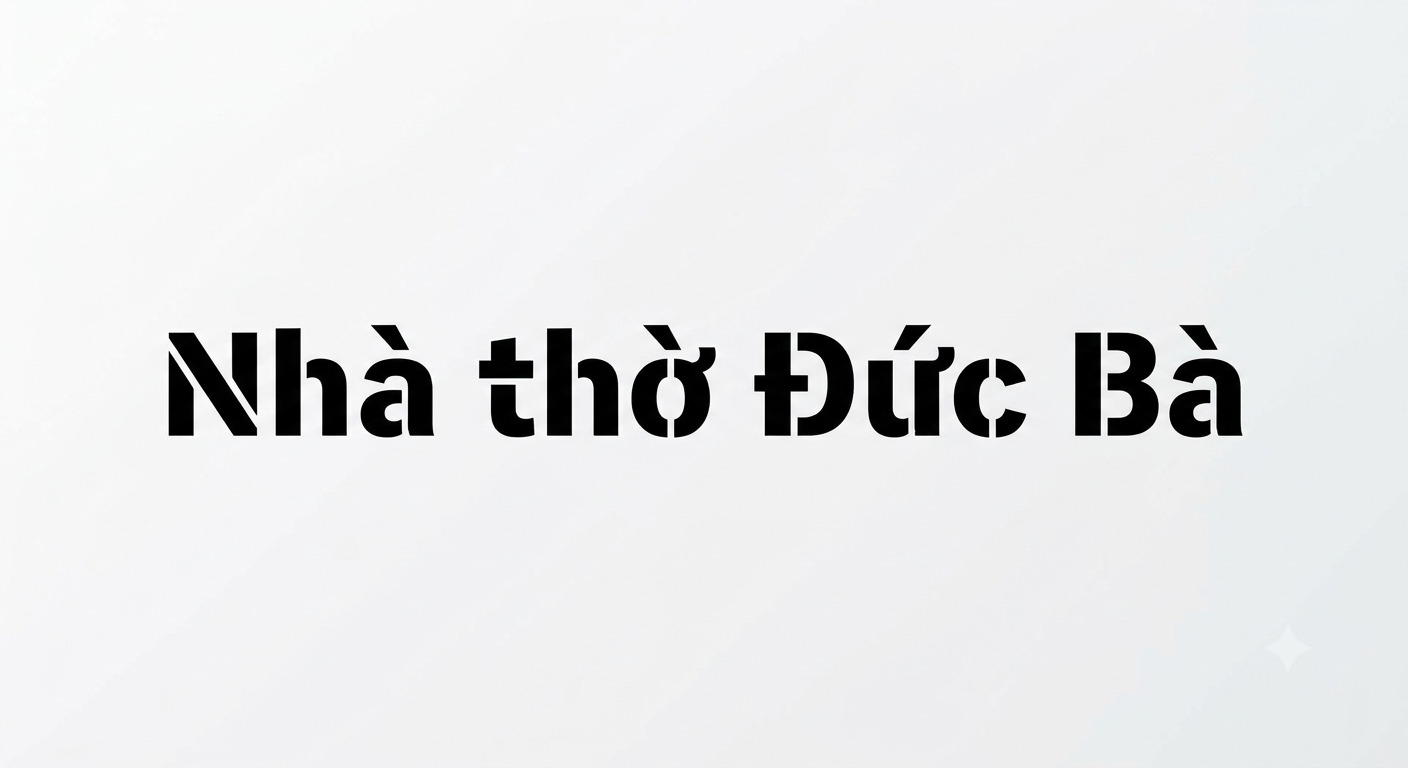
Font Stencil Việt hóa (hay còn gọi là phông chữ khuôn mẫu, nét đứt đoạn) là nhóm các phông chữ mô phỏng lại các ký tự được sơn xịt qua tấm khuôn (shablon) trên các thùng hàng vận chuyển quân sự và công nghiệp. Với đặc trưng là các đường nét bị cắt đứt quãng có chủ đích, phông chữ Stencil mang lại diện mạo thô mộc, mạnh mẽ, cá tính và đậm chất thực dụng. Doozypack.vn cung cấp link Tải Font Stencil trọn bộ chuẩn kỹ thuật, giúp bạn sở hữu phông chữ độc đáo này, hỗ trợ đầy đủ tiếng Việt để tự tin thiết kế bao bì, nhãn mác và bộ nhận diện thương hiệu.
Đặc điểm thẩm mỹ độc đáo của bộ font Stencil
Font Stencil không đi theo sự liền mạch của các phông chữ thông thường; nó tạo ra một ngôn ngữ thị giác đầy tính công nghiệp, gợi nhắc đến thế giới của logistics, quân đội và các xưởng cơ khí.
Phong cách cắt đứt (Stenciled) mang đậm dấu ấn quân sự và vận tải
Đặc trưng lớn nhất của Font chữ Stencil là các nét ngang và dọc bị ngắt quãng tại những điểm giao nhau. Kỹ thuật này vốn sinh ra để tấm khuôn kim loại không bị rơi rớt phần lõi khi khắc chữ lên thùng hàng. Trong thiết kế đồ họa, khoảng trống (gaps) này trở thành một điểm nhấn thẩm mỹ vô cùng đắt giá, giúp tiêu đề bản thiết kế toát lên vẻ gai góc, thực dụng và mang hơi hướng đường phố (Military & Streetwear).
Cấu trúc chữ vững chãi tối ưu cho các tiêu đề mạnh mẽ
Hầu hết các biến thể phổ biến như Font SVN Stencil đều sở hữu cấu trúc chữ in hoa (All-caps) với độ dày nét (weight) lớn. Trục chữ thẳng đứng vững chãi giúp các dòng tiêu đề giữ được độ dễ đọc tuyệt vời ngay cả khi được in trên các bề mặt thô ráp như thùng carton sóng hoặc túi giấy Kraft.
Ưu điểm nổi bật của bản SVN Stencil Việt hóa
Khi ứng dụng các phông chữ khuôn mẫu quốc tế vào thị trường trong nước, sự chỉn chu về dấu câu là yếu tố quyết định đến tính chuyên nghiệp của ấn phẩm:
- Khắc phục triệt để lỗi dấu tiếng Việt: Phiên bản SVN Stencil Việt hóa đã được đội ngũ thiết kế trau chuốt thủ công từng dấu câu. Các dấu sắc, huyền, hỏi, ngã, nặng được cắt đứt quãng đồng điệu cùng thân chữ gốc, không gây cảm giác chắp vá hay làm mất đi tính kỷ luật công nghiệp.
03 Ứng dụng thực tế của font Stencil trong sản xuất bao bì tại Doozypack.vn
Sự thực dụng và cá tính của Stencil mang lại hiệu ứng thị giác đắt giá trên các dòng sản phẩm bao bì thực tế do Doozypack.vn sản xuất:
- Hộp carton sóng đóng hàng & Vận chuyển: Tiêu đề và mã hiệu in bằng font Stencil màu đen trên thùng carton tạo nên diện mạo chuẩn mực công nghiệp, gợi cảm giác hàng hóa an toàn và chuyên nghiệp.
- Túi giấy thời trang Streetwear: Tên cửa hàng in bằng font Stencil trên nền túi giấy Kraft nâu tạo phong cách bụi bặm, nổi loạn và cực kỳ sành điệu cho giới trẻ.
- Nhãn dán chai Bia thủ công & Đồ uống năng động: Nét cắt Stencil giúp nhãn dán toát lên vẻ độc bản, thô mộc và thu hút sự chú ý ngay lập tức trên kệ hàng.